דמיינו גופן חי, עם צבעים מרהיבים, פונט שיכול להפיח חיים בכל טקסט. זהו הקסם של פונט SVG, צאצא קסום של פורמט OpenType ופלטפורמת Scalable Vector Graphics) SVG).
לגופני SVG יש את הכוח לשחרר את הפוטנציאל האמיתי של הטיפוגרפיה. עם היכולת להציג תווים במספר צבעים וברמות שקיפות, גופני SVG הם המורדים של עולם הפונטים, ומשתחררים מהמונוטוניות של הפורמטים הרגילים של הגופנים OTF ו-TTF. הם התגלמות גופני צבע, או כפי שהם ידועים גם, גופני OpenType SVG.
אבל, כמו בכל הדברים ששוברים את התבנית, גופני SVG מגיעים עם פשרה: גודל הקובץ שלהם עצום! הם מגיעים במשקל מאוד כבד שיכול להאט את קצב העבודה שלכם. הם ממש כמו היפופוטם בין הגופנים.
עם זאת, גודל זה הוא מחיר קטן לשלם עבור הפאר של גופני SVG. הם חלומו של מעצב ומעצבת, במיוחד כשמחפשים גופנים דמויי מברשת וכלים ידניים. עם היכולת שלהם להתמודד עם אזורים שקופים למחצה ואפקטים של צבעי מים, טושים, גואש, גיר ושאר טקסטורות מעניינות. גופני SVG משחררים את היופי האמיתי של האומנות הטיפוגרפית.
אז תנו לדמיון שלכם להשתולל, ותנו לגופני ה SVG לקחת את העיצובים שלך לגבהים חדשים!
בראוניז. גופן svg דמויי גיר
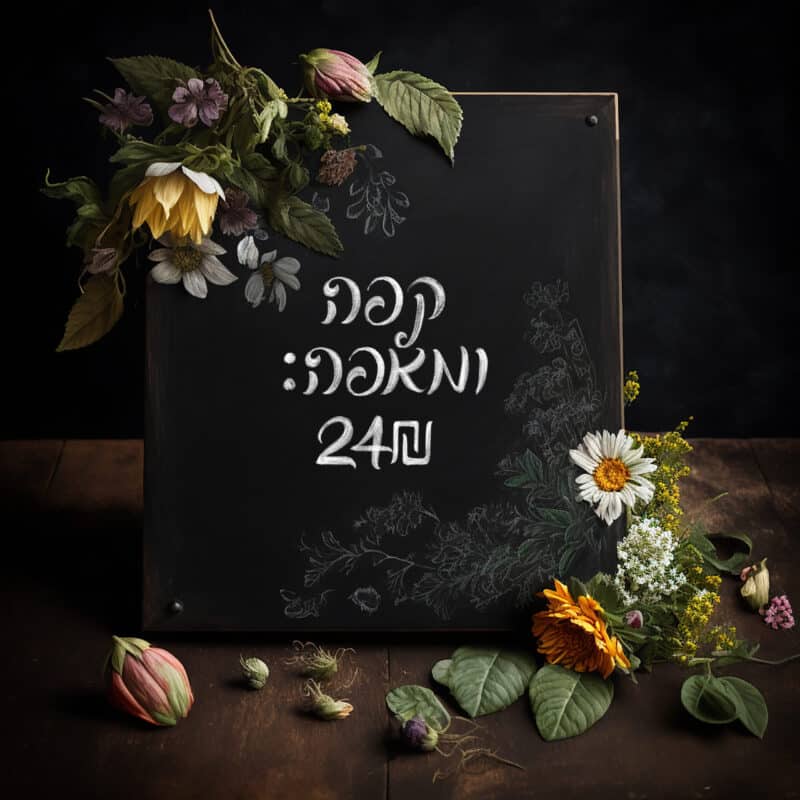
פונט Cardus Brush SVG:
פונט svg חינמי בסגנון מכחול צבעי מים:
איך פונט זה שונה מפונטים רגילים?
בניגוד לפונטים פונטים כתב יד בעברית המבוססים על קווים ומתארים (Outlines), פונטים מסוג SVG כוללים גרפיקה וקטורית מלאה, שיכולה לכלול צבעים, דפוסים ופרטים מורכבים יותר.